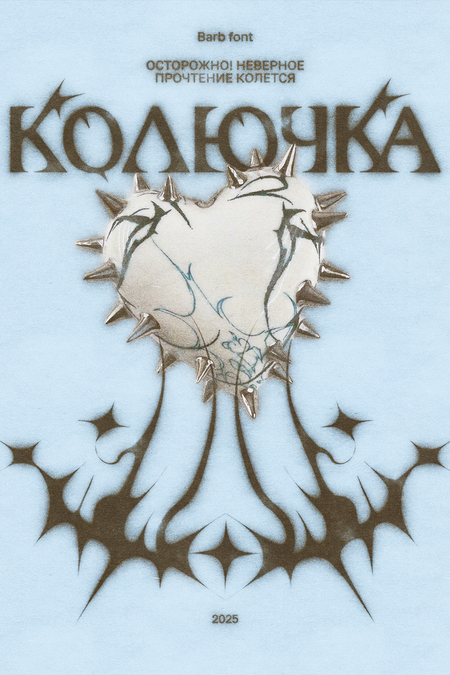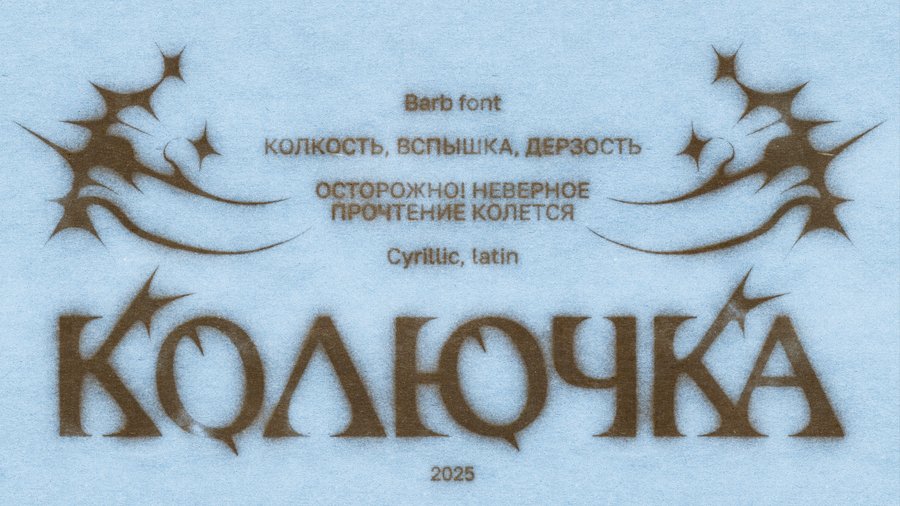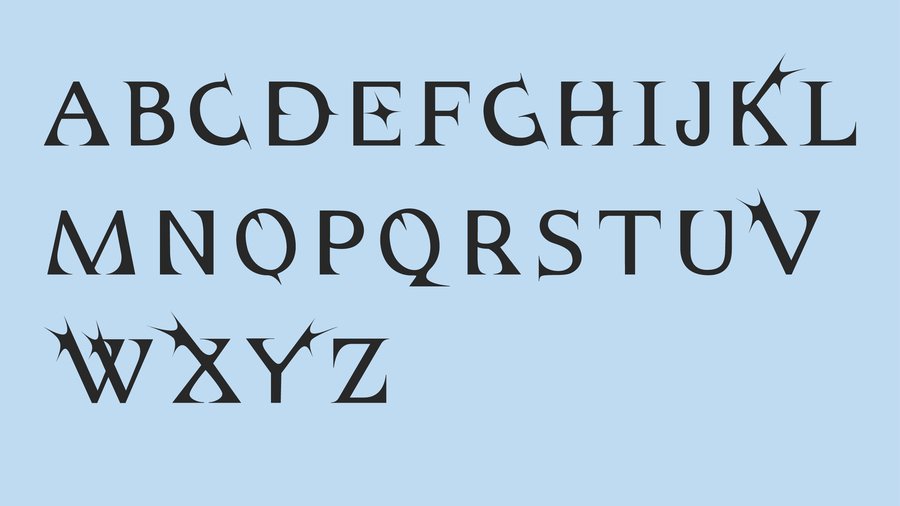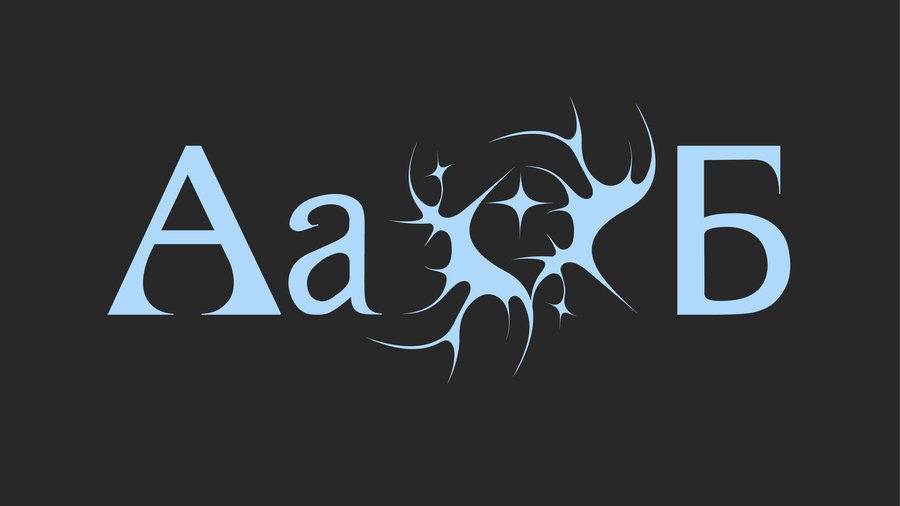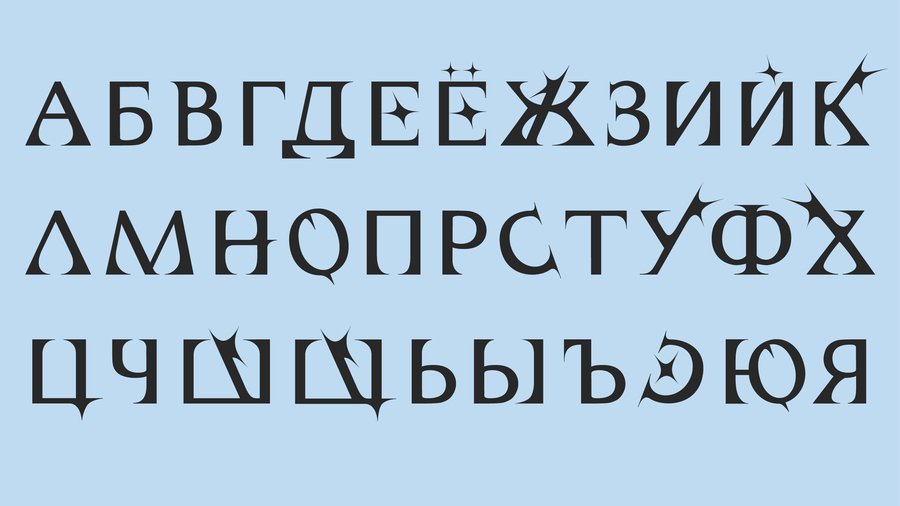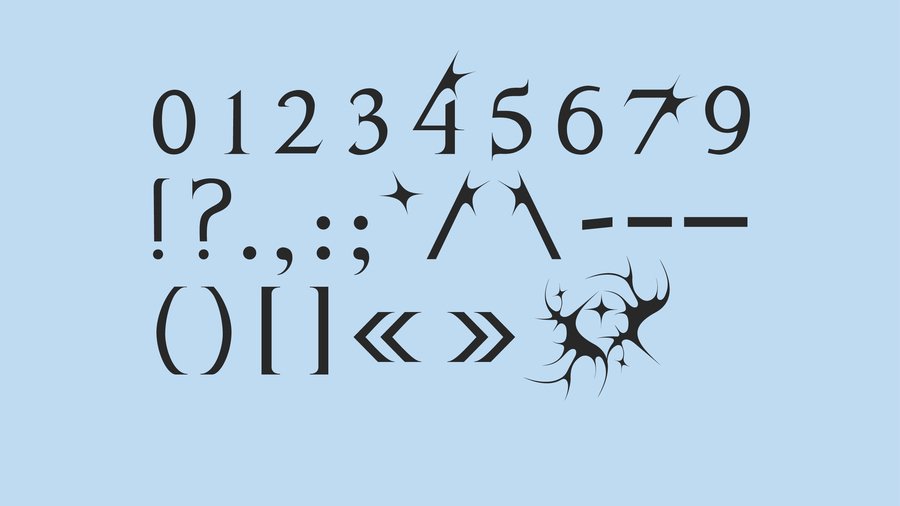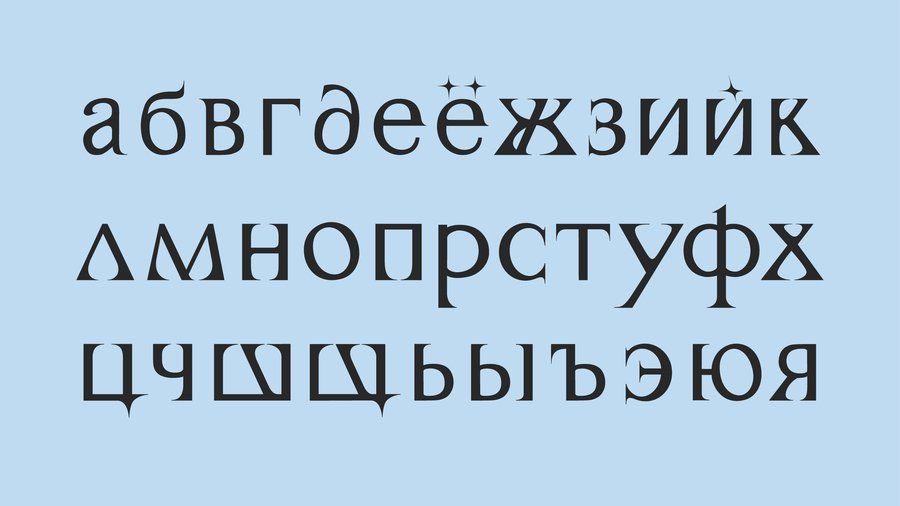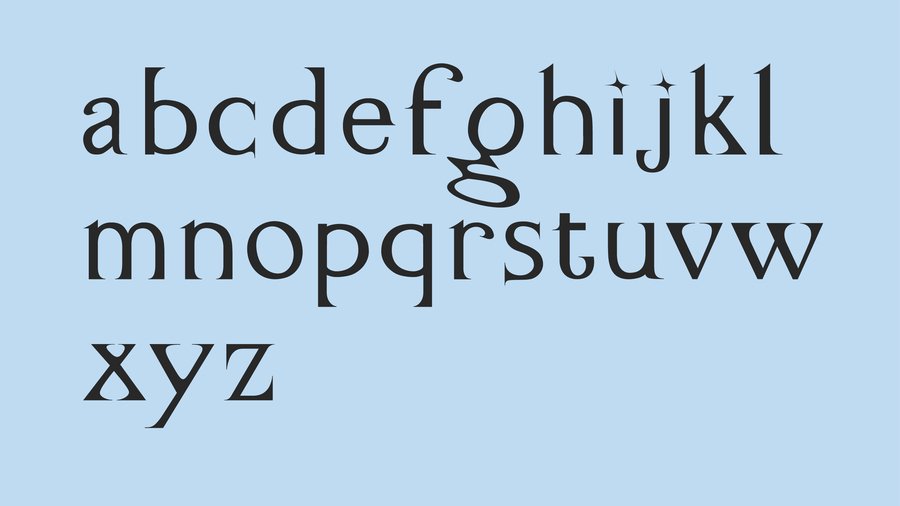
Barb Font / Шрифт Колючка, в котором дерзкий характер, вспышка света и клубная музыка воплотились в «колючках». Он резкий, колкий, дерзкий, а неверное прочтение этого шрифта может уколоть. Barb Font создан для бренда мультидисциплинарного арт-мейкера 54.43/20.30
54.43/20.30 создаёт уникальные произведения, которые заставляют зрителей задуматься о сильных эмоциях и личном опыте. Бренд художницы, сочетающей в своём творчестве татуировки, живопись и керамику